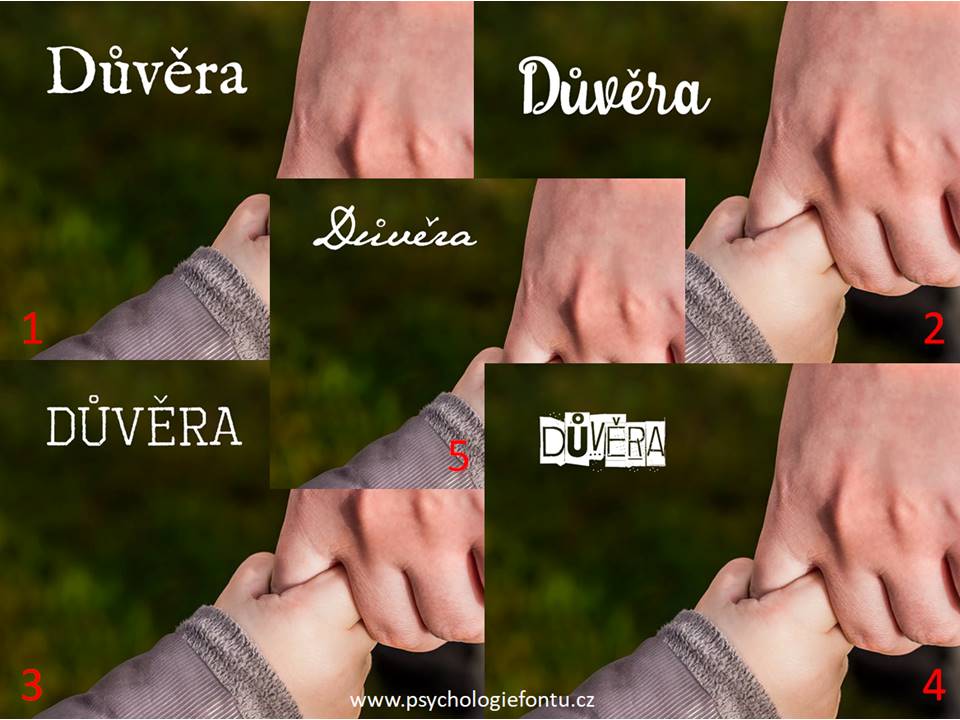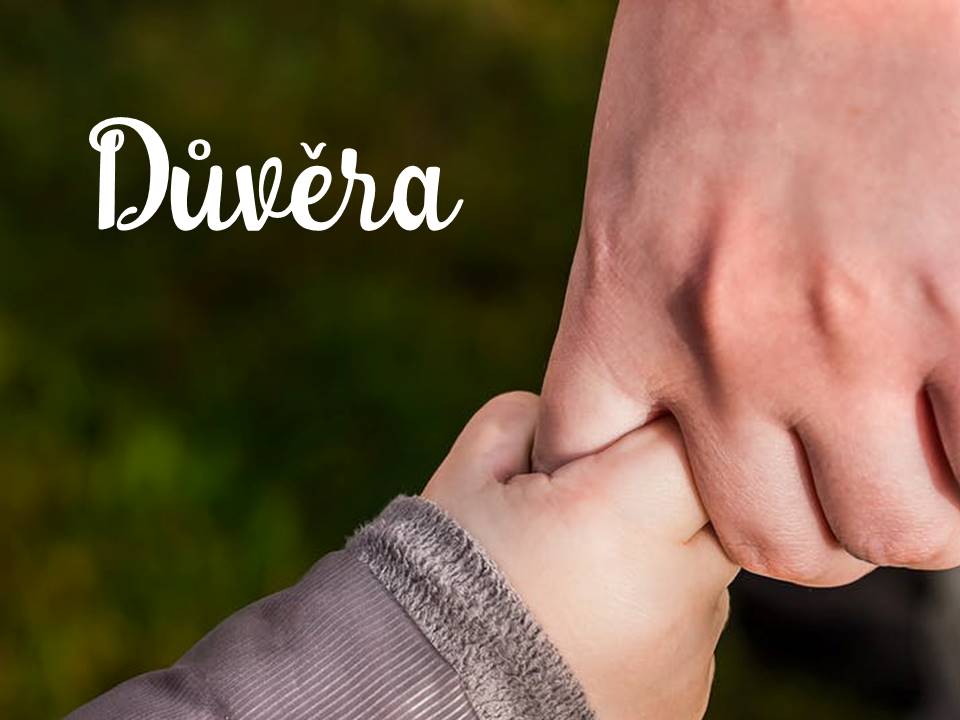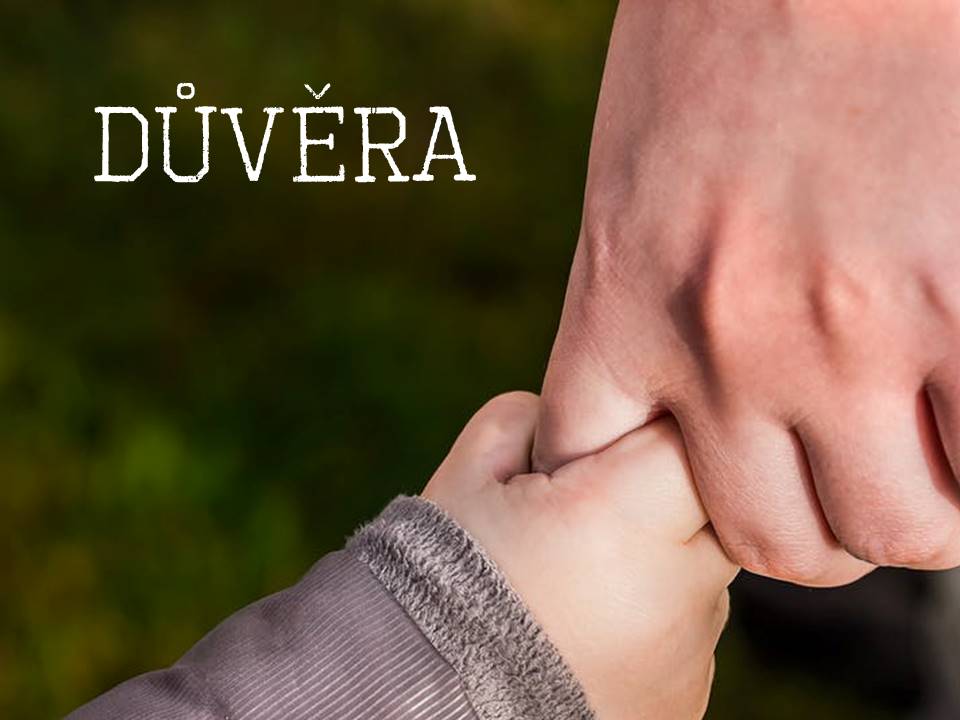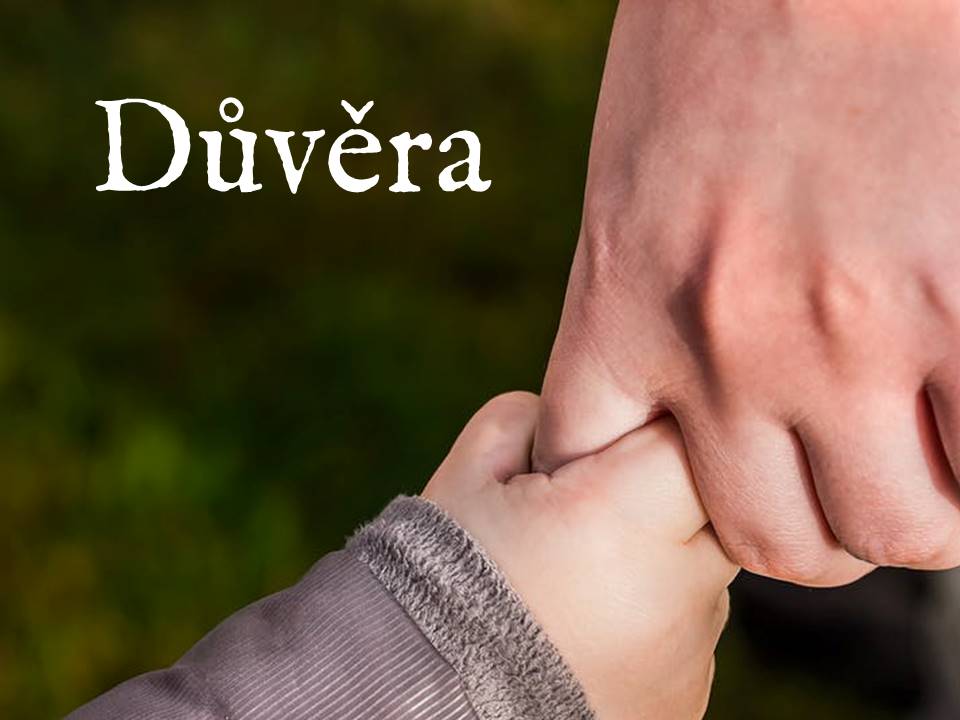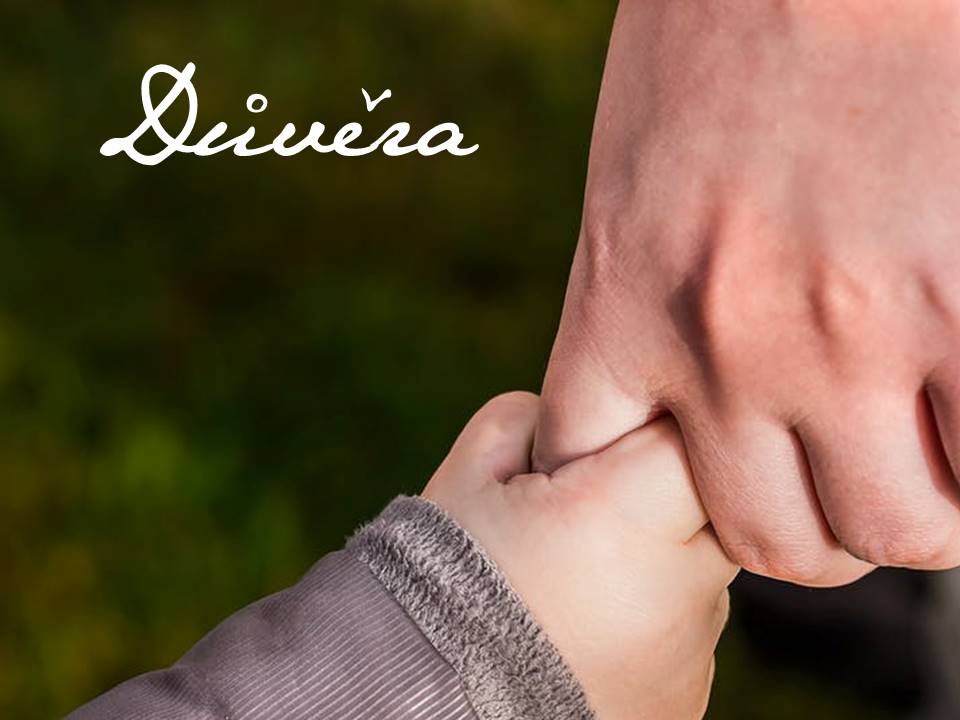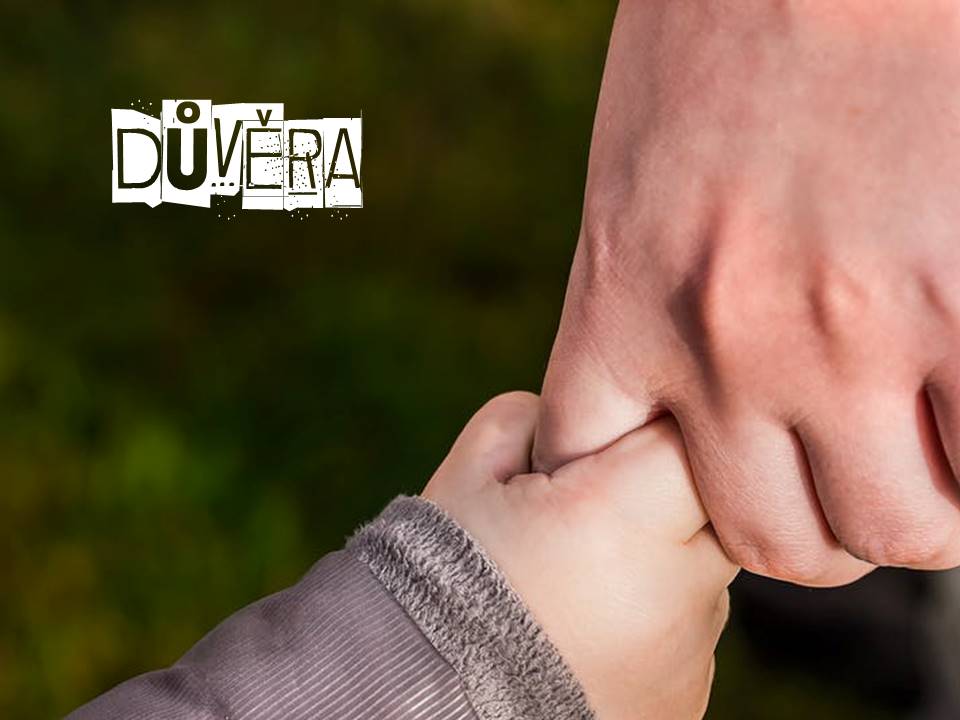
Málo emocí je tak křehkých a přitom tak silných. Na důvěře je postavené vše pro člověka důležité. Jak jste na tom vy? Věříte jen sami sobě, připadáte si často jako naivky anebo jste nevěřící Tomáš?
Zkuste řeč fontů, třeba vám prozradí, co pro vás důvěra znamená.
Pohodlně se posaďte a podívejte se na obrázek. Na obrázek klikněte, zvětší se vám a jedině tak ucítíte atmosféru každého fontu. Jeden font vám určitě bude sympatičtější než ostatní. Možná se nebudete umět rozhodnout mezi dvěma fonty, i to je v pořádku. Svět není černobílý ;-). Pod obrázkem najdete potom řešení co vám fonty o důvěře (a o vás) vypráví.
Vybrali jste si? Přečtěte si ke každému fontu řešení:
1 – Hluboká důvěra sám v sebe. Věříte ve své tělo, svou mysl a sebe sama. Věříte si natolik, že vás názory druhých nemohou rozhodit. Znáte své schopnosti a možnosti a důvěřujete svému instinktu. To vše vám umožní věřit lidem kolem vás. Bez závislosti, že potřebujete jejich uznání a bez slepé naivity. Dáváte jim prostor naplnit vaši důvěru, ale když vás zklamou, jdete dál, nezničí vás to. Stojíte totiž pevně nohama na zemi a ve své vlastní síle.
2 – Dětská naivní důvěra. Máte chuť někdy plakat do polštáře? Připadáte si jak z jiného vesmíru? Možná máte pocit, že jste někdy přespříliš naivní a důvěřiví. Máte velká očekávání, otevíráte se lidem kolem vás a někdy to prostě nedopadne. Neznamená to, že jste slabí. Jste jen zranitelní ve vaší potřebě věřit ostatním stejně nebo více než sami sobě. Potřebujete ujištění, potřebujete komunikovat. A věříte, že lidé kolem vás jsou dobří.
3 – Nevěřící Tomáš. Samotné slovo důvěra vás naplňuje nedůvěrou. Jak byste mohli někomu věřit, natož důvěřovat? Nemůžete se svěřit, dát svá tajemství a pochybnosti všanc druhým. Potřebujete pevná, jasná pravidla, řád a pouze v rámci nich jste ochotni připustit, že můžete zkusit důvěřovat. A někomu vylít své srdce? Nezapomenete zdůraznit, že je to jen mezi vámi, a necháte ho přísahat na smrt domácího mazlíčka, že nic nevyzradí.
4 – V nikoho a nic. Hrajete si se slovem důvěra, ale kloužete po povrchu. Zkoumáte ho shora, zdola, rádi ho používáte, ale co pro vás znamená? Dokážete naplnit jeho podstatu a svěřit se plně do rukou druhého? Nebo máte pocit, že důvěra se už nenosí a v kurzu je zpochybňování čehokoli a hledání vlastních cest? Možná je v tom jen váš strach připustit, že chcete věřit, chcete někdy ty starosvětské hodnoty gentlemanů, i když jsou nemoderní. Sundat masku „pohody“ a „jsem in“ a na nic si nehrát. Důvěra je zavazující, ale zároveň vás vytrhne z osamělosti.
5 – Věc cti. Důvěra? Ale to je samozřejmé. Na vaše slovo se může spolehnout každý. Ne proto, abyste druhé nezklamali, ale hlavně abyste nezklamali sami sebe. Jste zásadoví a dané slovo nikdy neporušíte. Máte své ideály a nenecháte se od nich odradit žádnou zradou, zesměšňováním nebo odstrkováním. O důvěře nemusíte mluvit, dávat ji na odiv nebo někoho o ní ujišťovat. Potřebujete ji mít uvnitř sebe, aby byl svět v pořádku.